6 Cara Mengubah Font Bio Instagram agar Makin Estetik
Bosan dengan tampilan profil Instagram yang gitu-gitu aja? Kreasikan halaman personalmu di media sosial dengan mengganti font tulisannya. Dengan begitu, tampilan profilmu akan terlihat lebih estetik, seperti ada tipografinya.
Bagaimana cara mengubah font bio Instagram? ini memang tidak bisa dilakukan secara default. Namun, kamu dapat memanfaatkan beberapa website atau aplikasi yang memang menyediakan layanan untuk mengubah tulisan di Instagram.
Cara mengubah font bio Instagram
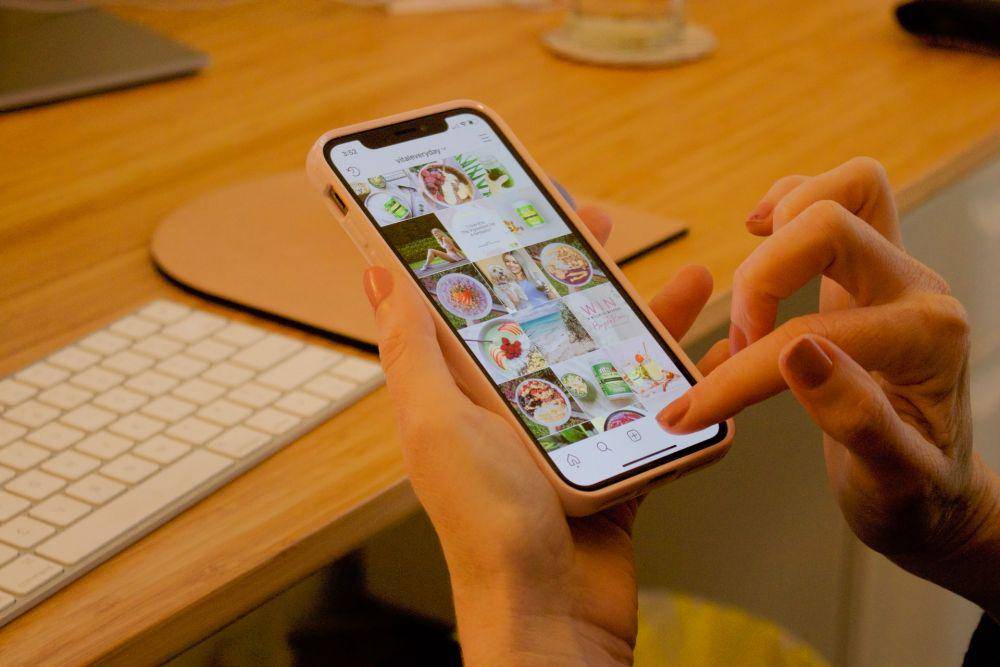
Pilihan pertama untuk mengubah font bio Instagram adalah dengan memanfaatkan website font generator. Kebanyakan dari situs berikut tersedia secara gratis. Hanya memerlukan jaringan internet yang stabil untuk mengaksesnya.
Cara menggunakannya pun sederhana. Cukup masukkan kalimat yang ingin kamu tampilkan di bio, pilih style tulisan dan biarkan generator mengubahnya. Tinggal salin dan sematkan di bio Instagram milikmu. Tutorial lebih lengkapnya di bawah, ya.
1. Meta Tags
Rekomendasi situs pertama yang bisa kamu gunakan adalah Meta Tags. Pada aplikasi ini, kamu dapat menemukan berbagai jenis font menarik, dari italic hingga mengombinasikan simbol-simbol estetik.
Meta Tags juga menyediakan preview sesuai teks yang ingin kamu tampilkan, lho! Begini cara pakainya:
2. Cool Symbol
Lanjut, yang kedua ada situs bernama Cool Symbol. Sesuai namanya, website ini menyediakan berbagai simbol menarik yang dapat digunakan untuk profil Instagram. Dari yang lurus hingga jenis font berkelok, semua ada.
Penggunaannya pun gak jauh beda dengan opsi cara mengubah font di bio Instagram sebelumnya. Berikut langkahnya:
Fitur lain yang menarik dari situs ini adalah kamu bisa mendekorasi teks sesuai keinginan. Caranya, pada langkah keempat, klik 'Decorate' terlebih dahulu.
Nantinya, kamu akan diarahkan ke jendela baru yang memberimu ruang untuk berkreasi. Mau ditambahin bintang-bintang? Bisa. Mau ada garis-garisnya? Boleh. Kreasikan saja sesuai kebutuhan.
3. Font Villa
Masih belum menemukan font sesuai keinginan? Move ke situs ketiga. Di Font Villa, kamu akan menemukan buanyak kombinasi huruf, simbol, bahkan emoji yang estetik. Saking banyaknya sampai bingung mau pilih yang mana.
Cara menggunakannya seperti berikut:
4. IG Fonts
Kalau ingin membuat kreasi huruf per huruf sesuai keinginan, maka IG Fonts jadi situs yang pas untukmu. Di sini, kamu gak cuma bisa memakai template yang ada, tetapi juga bisa membuatnya kombinasinya sendiri. Begini cara pakainya:
Jika memilih langkah keempat, kamu akan dialihkan ke jendela baru. Di sana, kamu dapat memilih style huruf satu per satu. Susunannya pun kamu sendiri yang mengaturnya, lho!
Ada preview teks di bagian atas. Kalau sudah selesai, tinggal klik 'Salin' dan tempelkan di profil Instagram-mu. Easy?
5. Font for Instagram
Cara mengubah font di bio Instagram tanpa aplikasi berikutnya yakni menggunakan situs Fonts for Instagram. Kelebihannya, website ini mengelompokkan font berdasar jenisnya. Jadi, makin mudah memilihnya, deh.
Untuk menggunakan situs ini, kamu tinggal melakukan langkah berikut:
Cara mengubah font di bio Instagram dengan aplikasi
Ada juga generator font yang berbasis aplikasi. Salah satunya yang populer yakni Fontify. Sebelum menggunakan, kamu perlu menginstal aplikasinya terlebih dahulu, ya. Begini langkah-langkah penggunaannya:
Jangan lupa ketuk centang di bagian pojok untuk menyimpan perubahan. Mudah gak, tuh?
Cara mengubah font bio Instagram ini tak hanya membuat profilmu estetik, tetapi juga berbeda dari pengguna lain. Tinggal kreasikan sesuai kreativitasmu, deh.